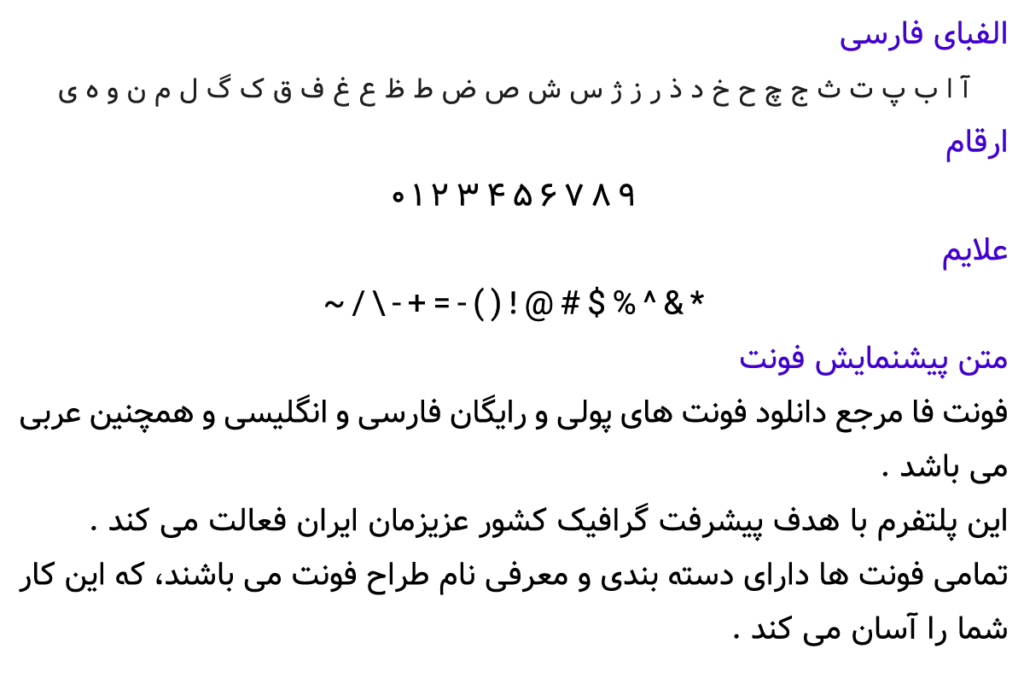
فونت فارسی ناهید – Nahid
طراح فونت: صابر راستی کردار نوع فونت: فونت متن
توضیحات و معرفی فونت ناهید
فونت فارسی ناهید ( Nahid ) از مجموعه فونت های آزاد می باشد، و نیز نوع فونت متن می باشد.
فونت خوشگل مربوط توسط صابر راستی کردار در سال 1395 طراحی و ساخته شده است.
آخرین نسخه 0.3.0 این فونت بر مبنای فونت وزیر متن و مشابه فونت گندم می باشد ولی با کمی تفاوت!!!
همچنین نسخه های لاتین این فونت با فونت انگلیسی Roboto ساخته شده است.
در این تصویر شعر با اصالت نام جاوید وطن را با تایپ فیس ناهید می توانید ببینید